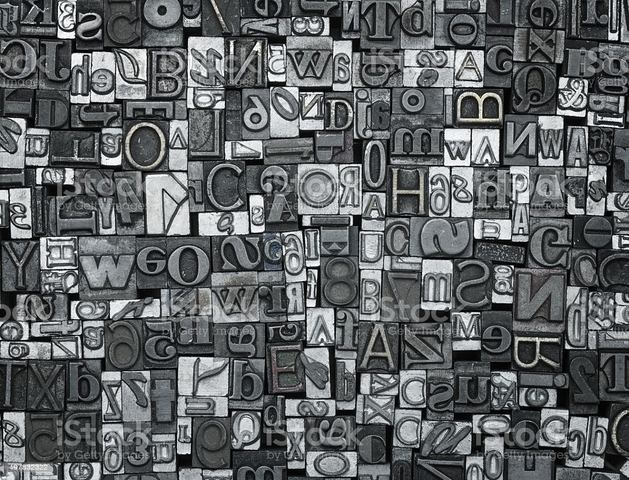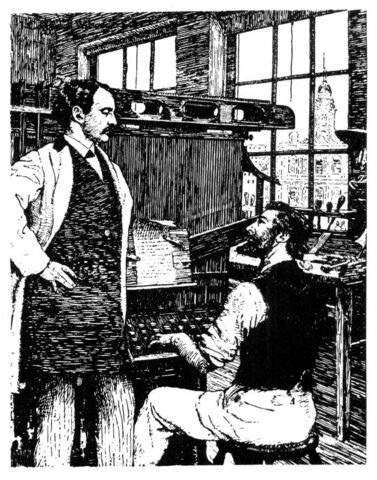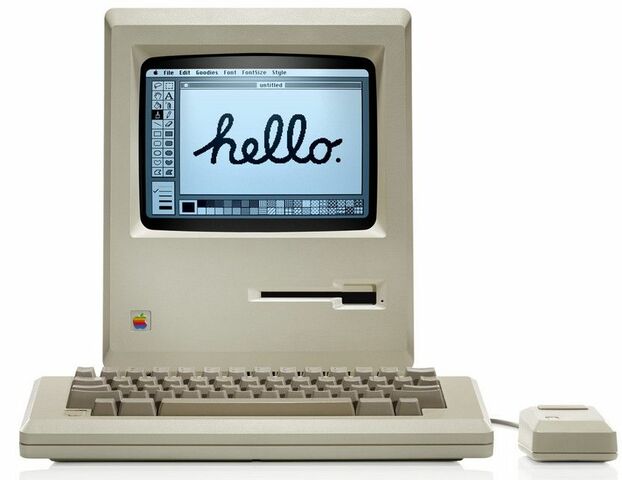
En 1692 el rey Luis XIV ordenó la creación de un comité de eruditos para el diseño de un nuevo tipo creado bajo principios científicos. El resultado fue la familia tipográfica Jaugeon, racionalista, con letras que mantienen un eje vertical perfecto y serifas horizontales simétricas.
Pierre Simon Founier, inició la estandarización del tamaño de las familias tipográficas al publicar su Primera Tabla de Proporciones.
Phillippe Grandjean modificó la tipografía Jaugeon, inspirándose en un nuevo diseño itálico conocido como Romain du roi Louis XIV. Esta labor continuó hasta cuando le remplazaron Jean Alexandre y Louis-René Luce.
A partir del principio del siglo XIX otra innovación importante en el mundo de la tipografía fue la aparición de las tipos sans serif. Aunque ya se habían visto en un catálogo publicado por William Caslon en 1816, no causaron un fuerte impacto hasta bastante tiempo después.
La tipografía Linotype, inventada por Ottmar Mergenthaler, y la Monotype, de Tolbert Lanston.
La litografía offset hizo que los tipos de metal fundido desaparecieran de la circulación y la venta de los primeros Apple Macintosh, mostraron un sistema operativo en los que se podían escoger diferentes tipos de letra para su aplicación en hojas de texto.